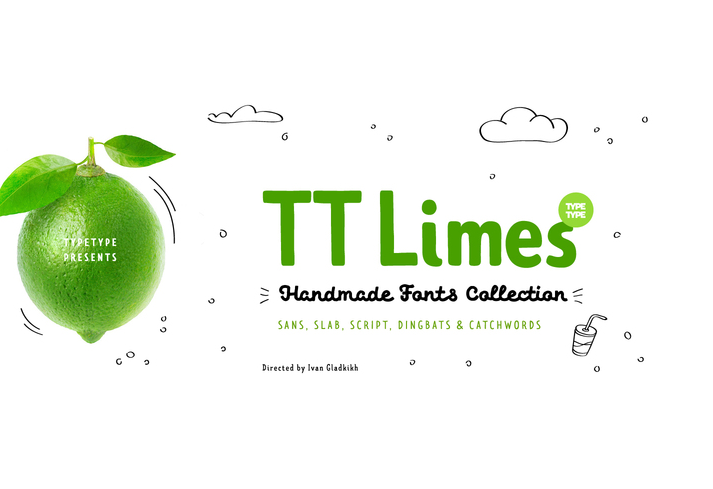
TT Limes Slab Regular Font
Sobre uma bela tarde no litoral naquele outono brasileiro, surgiu a ideia para uma nova família de fontes. A TT Limes Font Family nasceu da inspiração desse local encantador e das intenções do seu designer, Hamilton. Este projeto veio à tona durante um dia em que o sol iluminava as ondas da praia, fazendo-nos pensar em como podíamos trazer mais vida para nossas vidas diariamente cansadas no frio inverno brasileiro. A TT Limes é uma família de fontes serifada de estilo slab. Ela surge com a ideia de refrescar nossa rotina cotidiana com elementos suaves e vivos do verão, especialmente durante os meses mais frios do ano. Essas são as fontes que queremos lembrar quando o inverno faz sua estreia em nossas vidas: aquela sensação acolhedora de um sol se por, seguida pelo frescor da brisa de verão que chega finalmente, iluminando nosso caminho através do frio. TT Limes é a promessa de uma nova temporada de vida, mesmo quando o clima está mais difícil. A fonte é perfeita para quem busca algo acolhedor e vivaz em seu design gráfico diário, proporcionando um toque especial na comunicação visual durante os dias frios do inverno brasileiro.